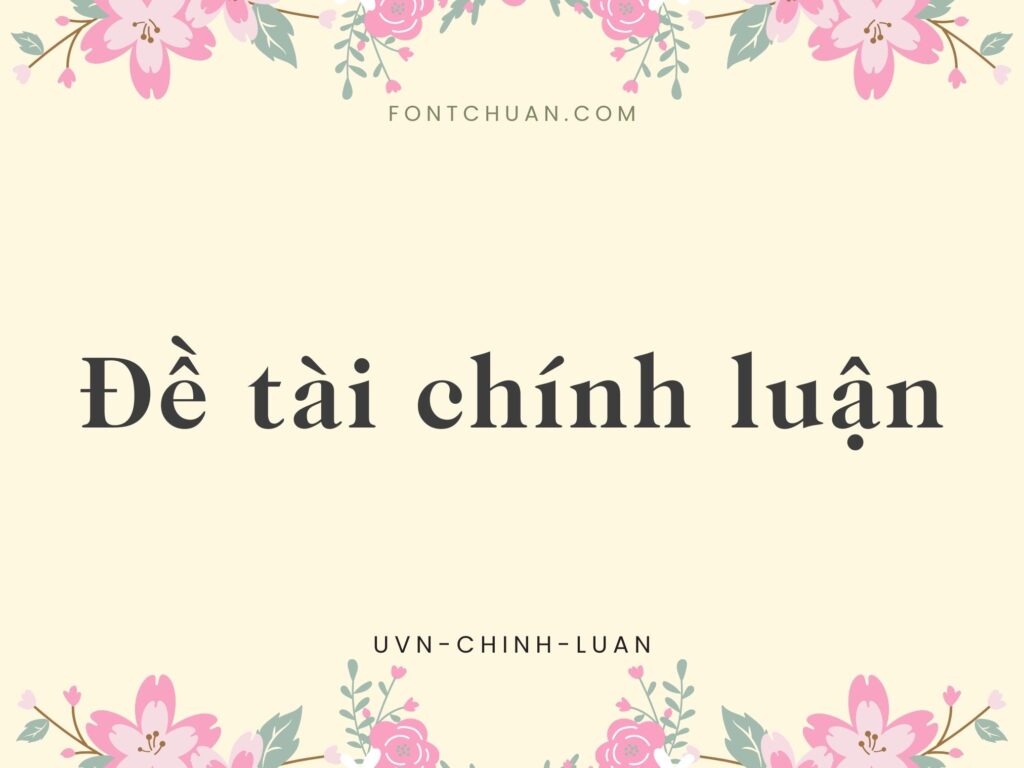
Font UVN Chinh Luan Việt Hóa
UVN Chính Luận là một kiểu chữ serif truyền thống mang đậm phong cách báo chí và học thuật, thường xuất hiện trong các ấn phẩm chính luận, tài liệu lịch sử và giáo dục. Với phong cách chữ rõ ràng, cổ điển nhưng không kém phần trang trọng, font mang lại cảm giác tin cậy và chuyên nghiệp. Font này chỉ được sưu tầm và đăng bởi thành viên của Font Chuẩn để phục vụ cho những dự án cần độ chuẩn mực cao trong thiết kế nội dung.
UVN Chính Luận có cấu trúc serif tiêu chuẩn, các đường gạch chân chắc chắn, độ tương phản trung bình giữa các nét dày mảnh. Font rất phù hợp cho tiêu đề bài báo, sách lịch sử, tài liệu giáo dục, thiết kế tạp chí hoặc brochure học thuật. Các ngành nghề phù hợp bao gồm giáo dục, công nghệ, bất động sản, quảng cáo và ẩm thực. Font này ứng dụng tốt trong các sự kiện như ngày Nhà giáo, Tết, lễ hội hoặc Trung thu.